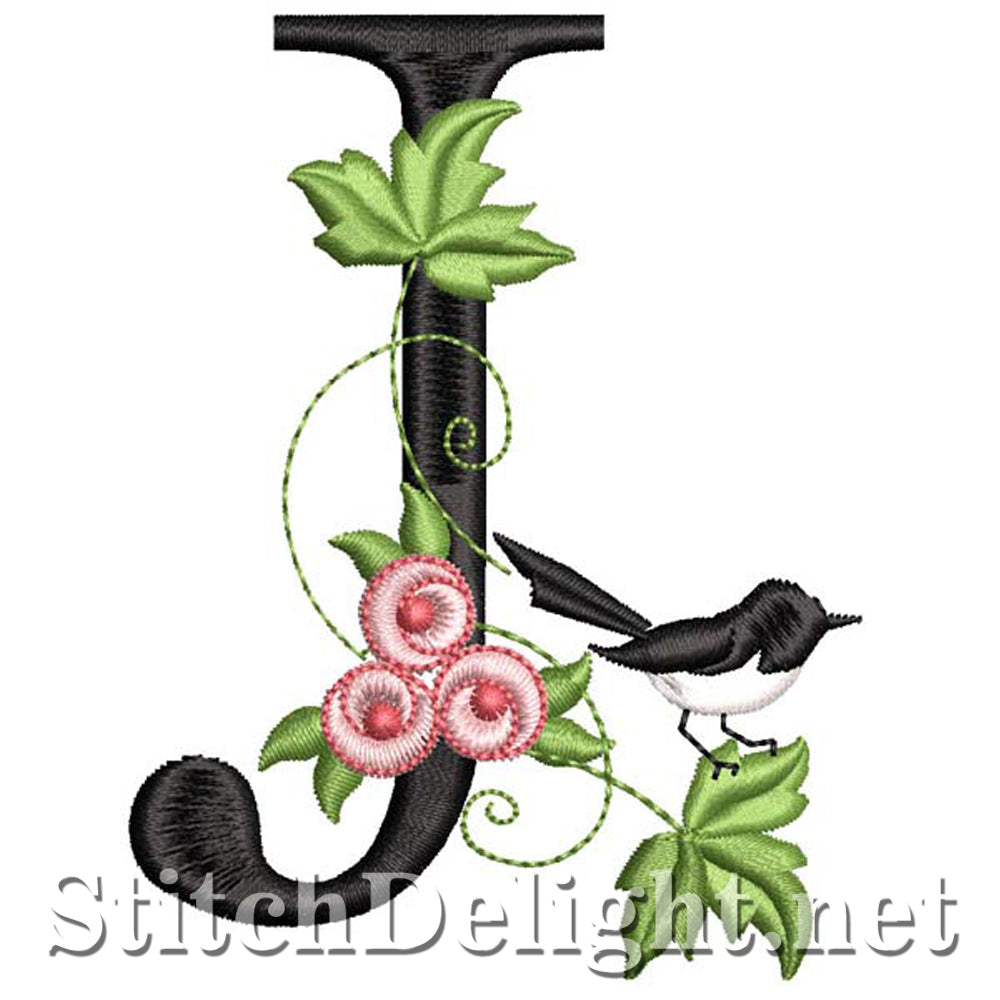
SDS1261 Little Tweets Police J
Jolies lettres décorées de petites roses en lingots et de minuscules oiseaux chanteurs - La hauteur des lettres est de 3,30" et le nombre approximatif de points est de 6200 points - CLIQUEZ sur l'image pour voir toutes les lettres de l'ensemble